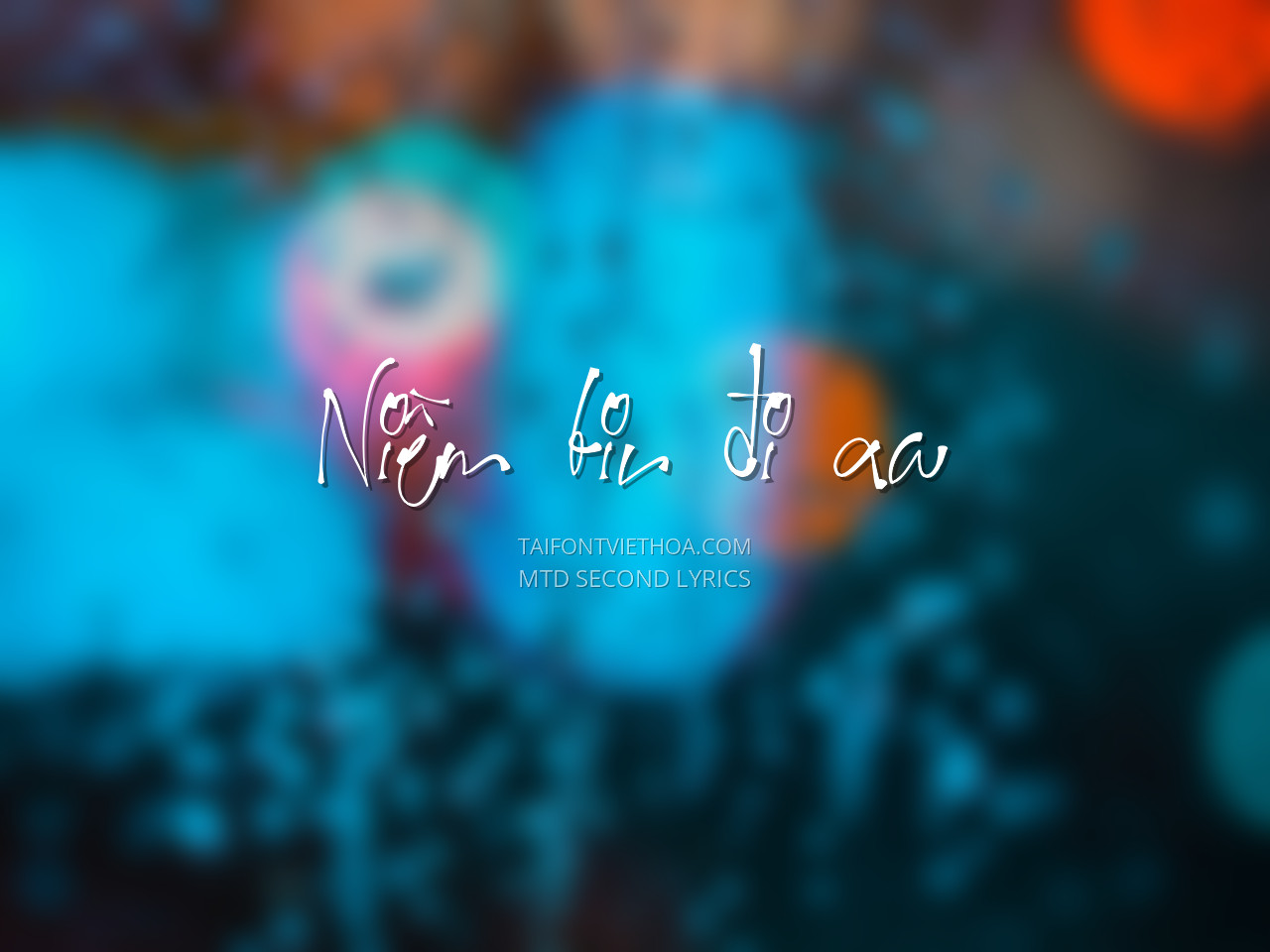
Font việt hóa MTD Second Lyrics
Tác giả Font: Mans Greback
Giới thiệu về font Second Lyrics
Second Lyrics là một font script mang phong cách nghệ thuật và đầy chất thơ, được thiết kế bởi Motokiwo Type (MTD) – studio nổi tiếng với các bộ font viết tay sáng tạo dành cho thiết kế cảm xúc. Font mang đến cảm giác như những dòng viết tay trong nhật ký, lời bài hát hay bưu thiếp cá nhân, vừa bay bổng vừa gần gũi. Nét chữ nghiêng nhẹ, mềm mại cùng các ký tự uốn lượn tạo nên tổng thể hài hòa, phù hợp cho các thiết kế truyền tải sự tinh tế và lãng mạn. Phiên bản Việt hóa do chính MTD thực hiện, hỗ trợ đầy đủ tiếng Việt và hơn 70 ngôn ngữ khác, tối ưu cho cả thiết kế in ấn lẫn kỹ thuật số.
Đặc điểm thiết kế và ứng dụng của font Second Lyrics
Second Lyrics nổi bật với cấu trúc chữ mềm mại, ligatures và swashes nhẹ nhàng, dễ đọc và dễ ứng dụng. Độ dày nét chữ vừa phải, giúp font vẫn nổi bật trong thiết kế thiệp mời, bìa sách, hoặc dòng tiêu đề ngắn. Các ký tự viết tay được xử lý cẩn thận để tạo cảm giác mượt mà và tự nhiên khi đặt trong văn bản thực tế.
Font rất phù hợp với các ứng dụng như: thiệp cưới, lời mời sự kiện, blog cá nhân, thiết kế thương hiệu thời trang nữ, tiêu đề cảm xúc, hoặc typography trên mạng xã hội. Ngành nghề lý tưởng gồm: cưới hỏi, làm đẹp, thời trang, truyền thông nghệ thuật, handmade và quảng cáo hướng đến phái đẹp.